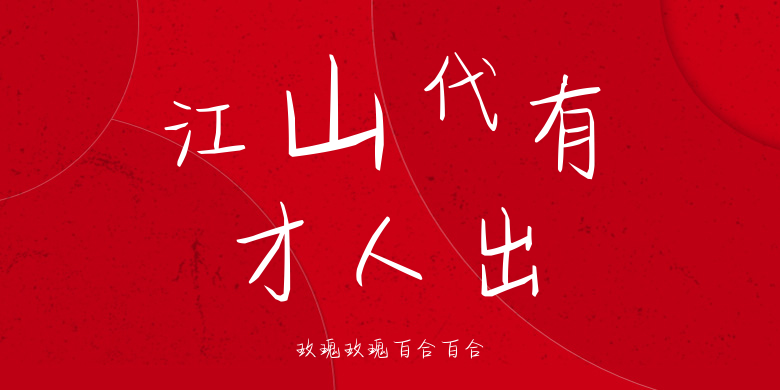
玫瑰玫瑰百合百合
玫瑰玫瑰百合百合,这款字体结构工整、笔画清晰,兼顾美观与易读性,适用于标题、正文、海报、包装、LOGO 等多种场景。字形优雅稳定,风格百搭耐看,适配日常排版与创意设计,让文字呈现更舒适、更具质感。玫瑰玫瑰百合百合一笔一画,皆是细节,以均衡的比例、流畅的线条打造舒适视觉体验,字形端正大气,风格简约现代。无论是商业设计、品牌宣传还是日常排版,都能轻松驾驭,让文字更有格调与力量。玫瑰玫瑰百合百合字体下载。